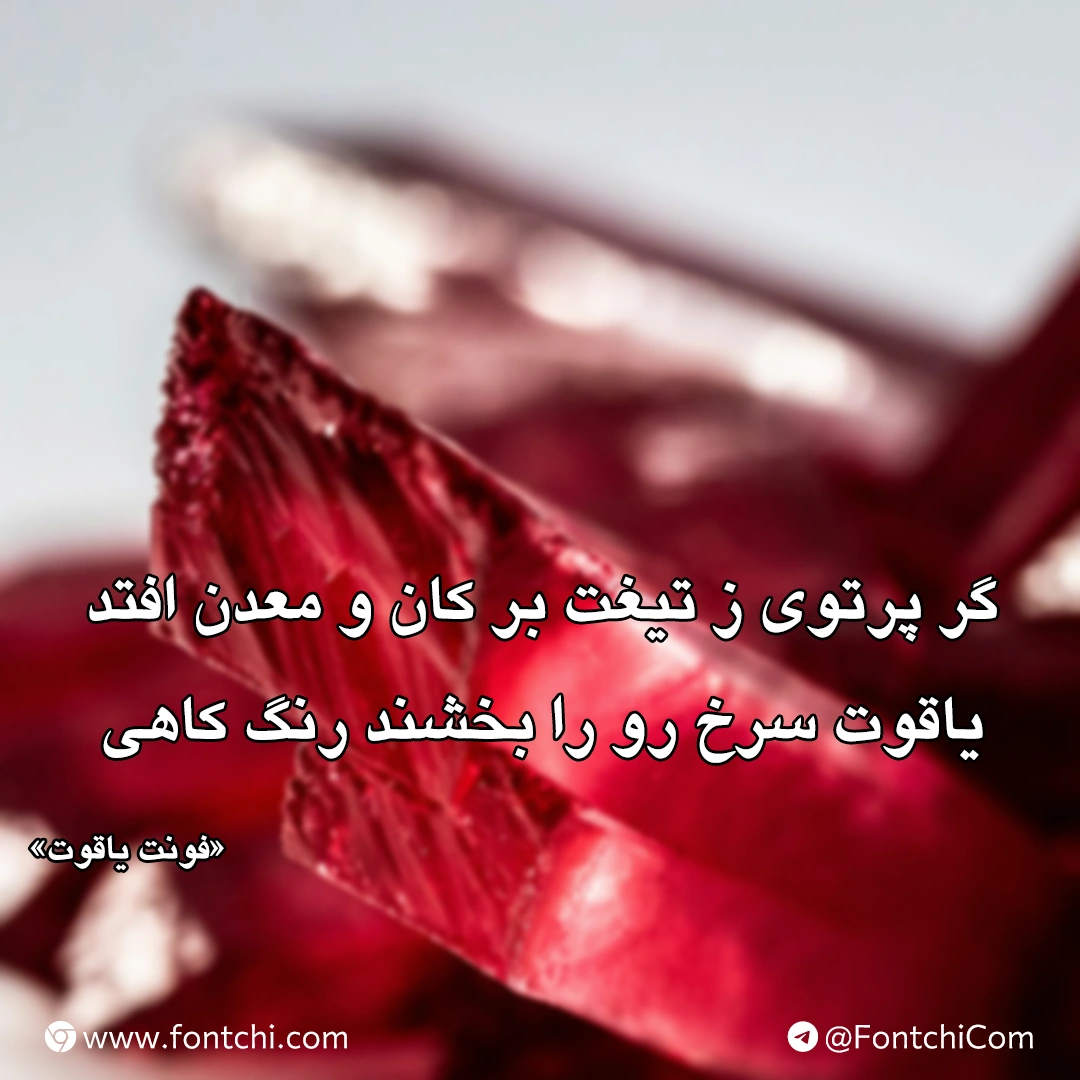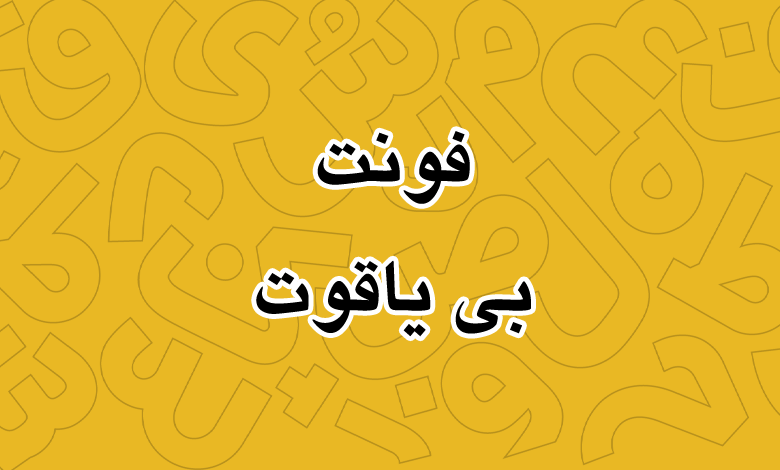
فونت بی یاقوت (B yagut)
فونت بی یاقوت (به انگلیسی: B yagut) یکی دیگر از قلمهای آزاد طراحی شده در دهه ۷۰ است که میتوانید از آن برای متون کوتاه تا بلند استفاده کنید. این فونت که از سبک نسخ بهره میبرد برای استفاده در مطبوعات و نامههای اداری گزینه خوبی محسوب میشود. در ادامه با دانلود رایگان فونت بی یاقوت همراه شما هستیم.
فونت بی یاقوت توسط برنا رایانه طراحی شده است و بر خلاف عموم فونتهای این سازنده، از دو وزن معمولی و بولد پشتیبانی میکند.
فونت فارسی بی یاقوت از زبان فارسی و عربی پشتیبانی میکند. تنها ایرادی که در این فونت وجود دارد بخش اعداد است که اعداد «۰۴۵۶» برای زبان فارسی نیز با ظاهر عربی تایپ میشوند که در این صورت پیشنهاد میشود از دیگر فونتهای سری B که دارای سبک نسخ هستند برای تایپ اعداد فارسی استفاده کنید.
فونت بی یاقوت میتواند برای استفاده در مطبوعات بهویژه چاپ روزنامه، مجلات و همچنین کتب گزینه مناسبی باشد. بیشترین استفاده از این فونت در متون کتاب مورد استفاده قرار میگیرد که دلیل آن پشتیبانی از دو وزن هماهنگ است.
این فونت فارسی برای کپ کات در ایفون نیز انتخاب خوبی خواهد بود که با توجه به پشتیبانی از دو وزن معمولی و بولد، امکان نوشتن متن با دو وزن را در ویدئوها به شما خواهد داد.